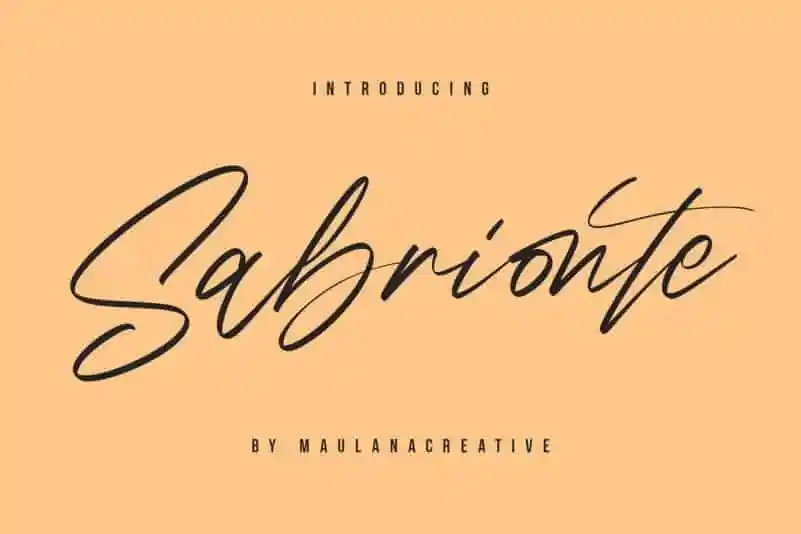
Sabrionte Script Font – Download Grátis
Olha quem está aqui! Introduzimos a Sabrionte Script Font, uma escolha ideal para qualquer designer que busca estilizar seu trabalho de maneira única e contemporânea. Esta nova fonte é perfeitamente projetada para complementar outras serifas tanto em design de logo ou identidade visual, quanto nas páginas de um site. As letras manuscritas da Sabrionte foram cuidadosamente criadas para fornecer uma sensação autêntica e única. Repleta de personalidade, a Sabrionte Script é perfeitamente adaptada para variados usos gráficos. Faça as marcas do seu site brilharem com o estilo elegante da fonte, use-a nas etiquetas de suas camisetas ou até mesmo nos rótulos de seus produtos em embalagens personalizadas. Seja qual for o projeto que você está trabalhando, a Sabrionte Script Font é um complemento perfeito para qualquer trabalho de design.